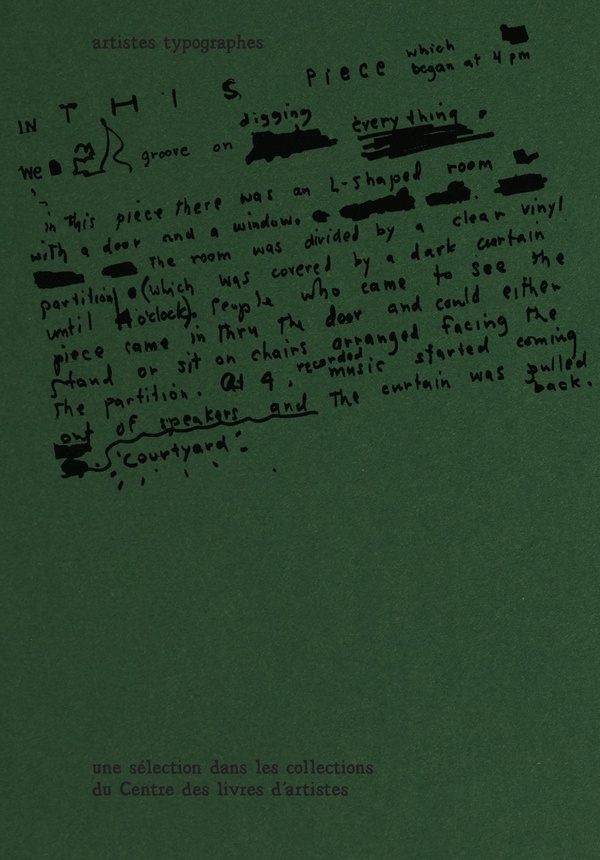
ARTISTES TYPOGRAPHES
Artistes typographes. Artistes typographes est un corpus visuel qui réunit cent trente-deux livres d'artistes collectés et reproduits dans le cadre d'une résidence artistique menée au sein du Centre des livres d'artistes (Saint-Yrieix-la-Perche). Les images présentées témoignent de l'intérêt de quelques figures du milieu de l'art pour les matières de l'objet livre. Elles orientent le regard sur des compositions singulières et autres détails typographiques : lettrages manuscrits, dessins de caractères, tampons, logotypes.